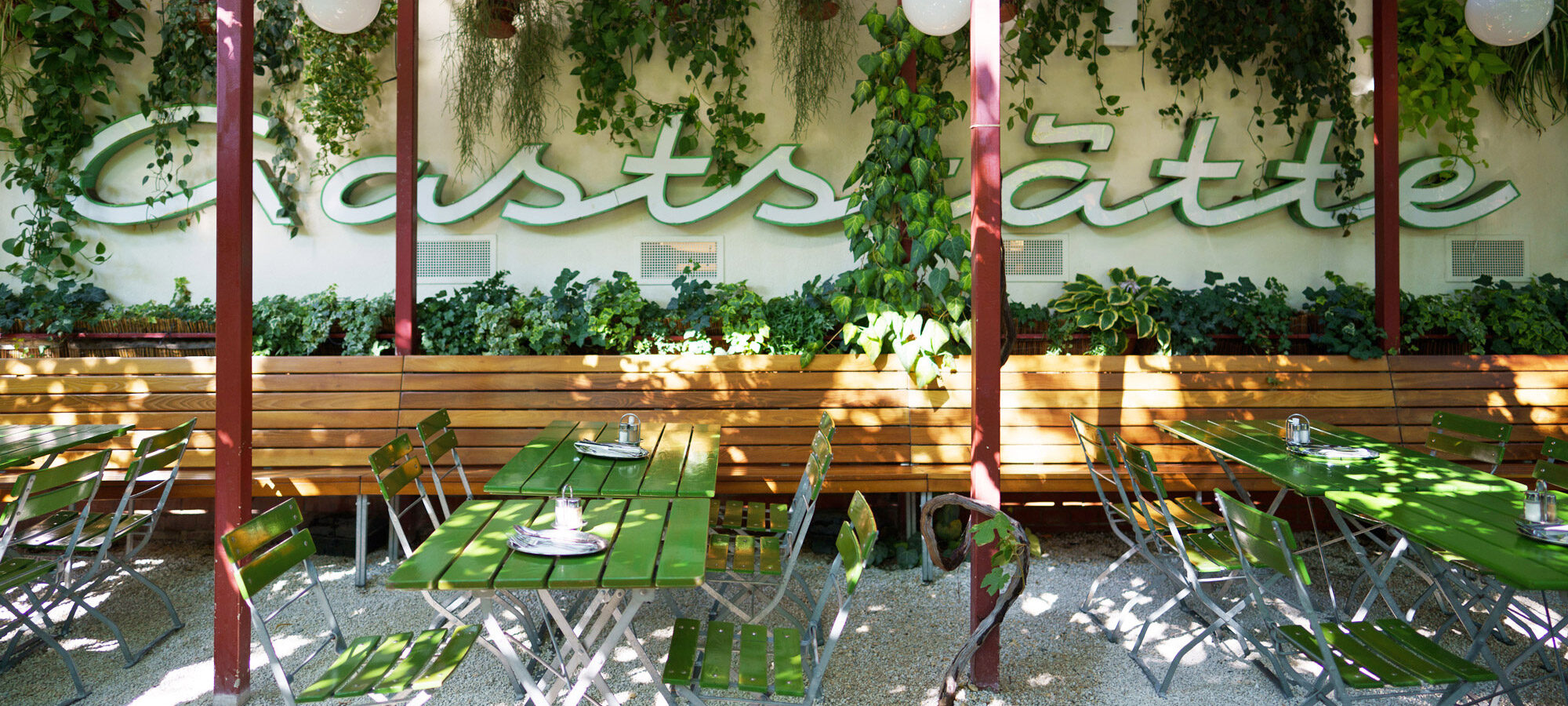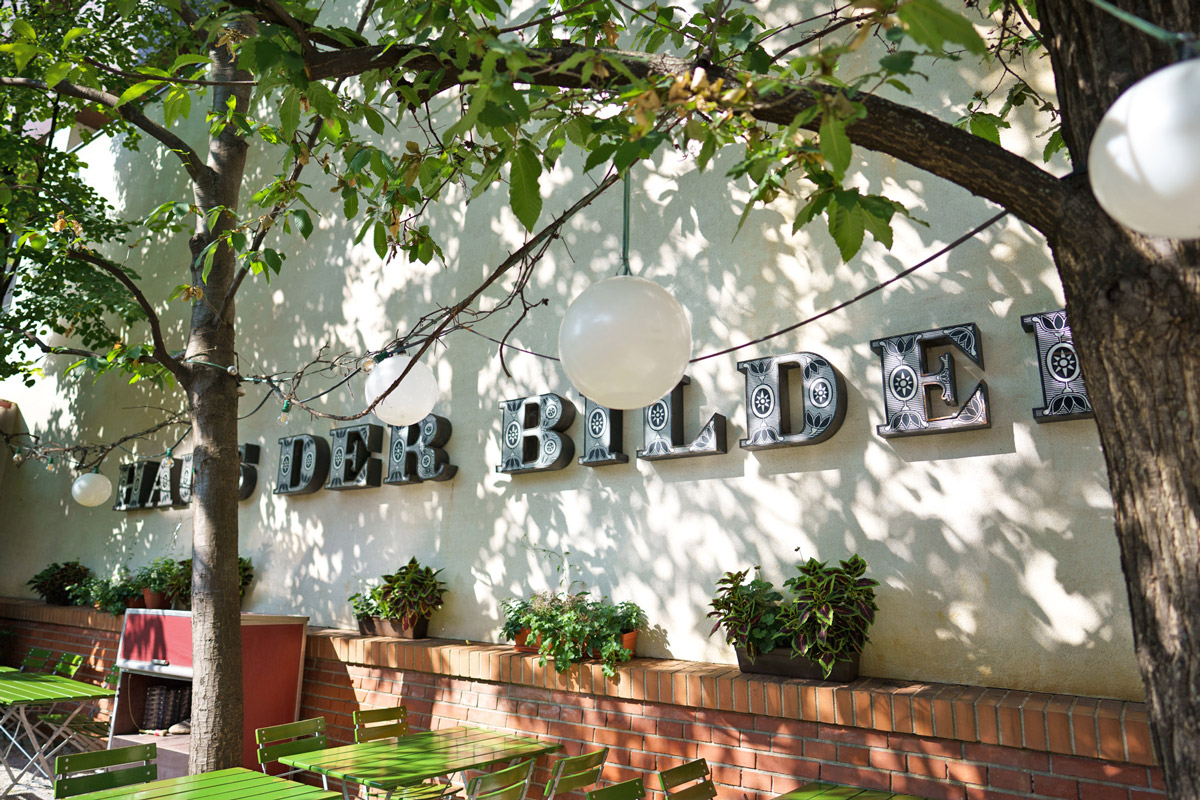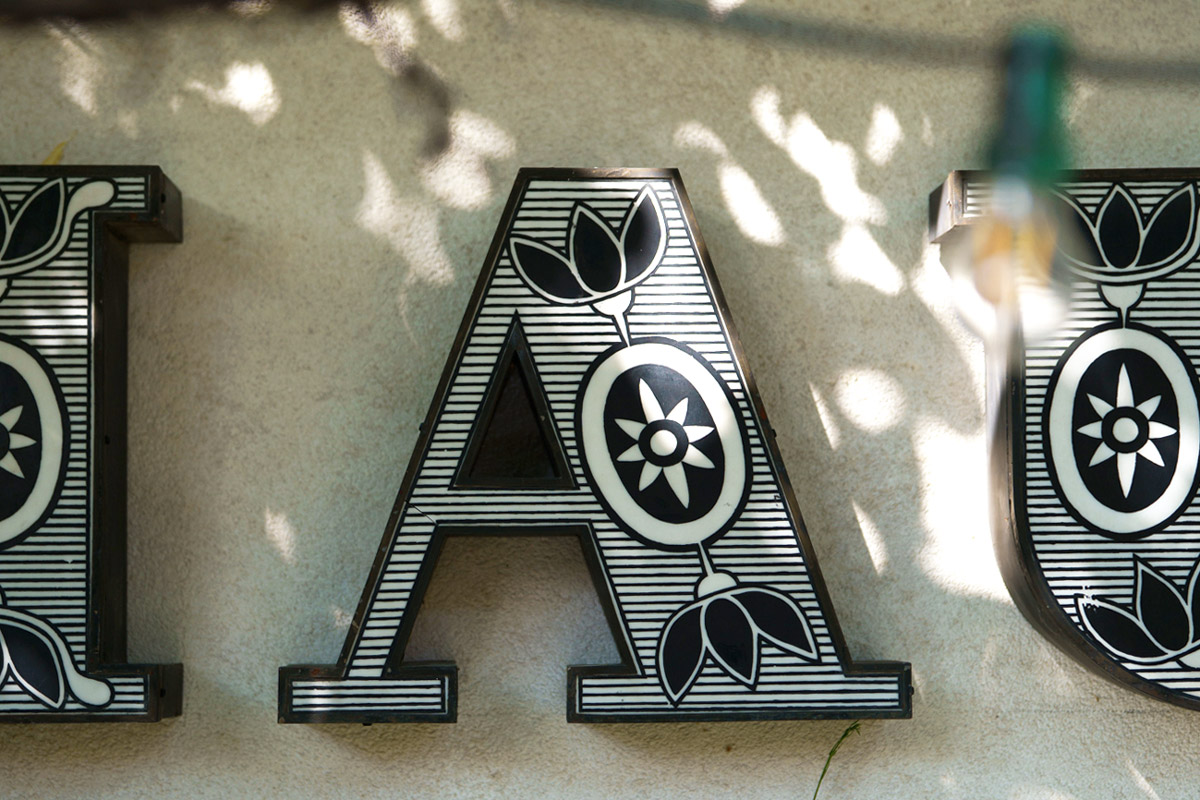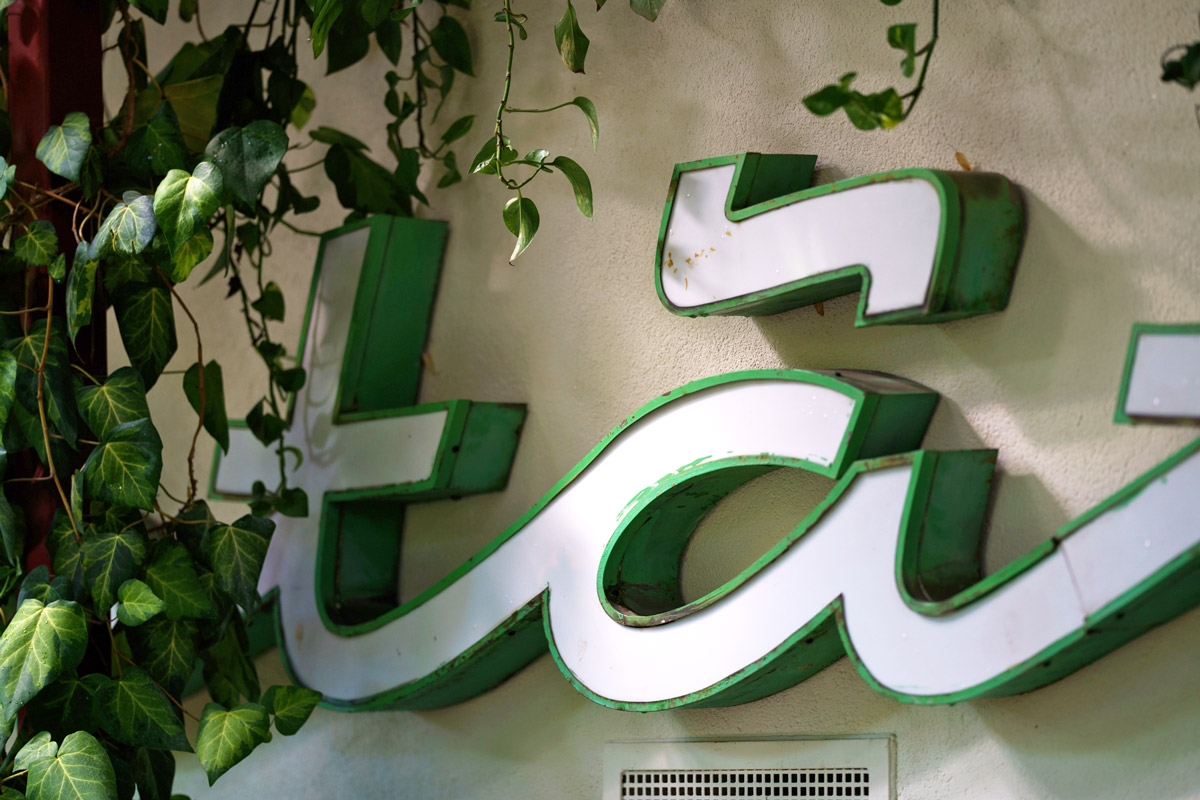
Stadtschrift im Glacis Gastgarten
Seit 2004 wird im Glacis Beisl am Spittelberg die Wiener Wirtshauskultur gepflegt, als Ort des Genusses, des Austauschs und der Beständigkeit inmitten eines sich wandelnden urbanen Raums. Wir wurden 2025 eingeladen, die langen Wände des Gastgartens mitzugestalten. Neben dem aus Hernals stammenden Gaststätte-Schriftzug wurde dafür das HAUS DER BILDER ausgewählt, das ursprünglich seinen Platz in unmittelbarer Nähe, an der Rückseite des Nachbargebäudes in der Breite Gasse hatte.
Gaststätte Schmidt
Schon um 1890 wurde in diesem Haus eine Gastwirtschaft betrieben, das Gasthaus »Zum Ölberg«. Die Hernalser Hoteliersfamilie Jäger führte den Betrieb bis 1954, als Johann Schmidt die Konzession übernahm. 1982 ging die Gaststätte an dessen Sohn über. Vermutlich zu diesem Anlass wurde die „Gaststätte Weinhaus Schmidt“ Beschriftung installiert, in zu dieser Zeit vorherrschender Ausführung mit innenliegenden Leuchtstoffröhren. Mangels Nachfolger kam es 2012 zur Schließung und ein Kindergarten zog in die Räumlichkeiten ein.
Haus der Bilder
Der Kunstsammler Helmut Klewan war als Galerist seit den 1970ern in Wien und München aktiv. Im »Haus der Bilder« zeigte er ab 2004 monatlich neue Ausstellungen mit Werken aus seiner Sammlung. 2012 wechselte das Haus den Besitzer. Eine geplante Renovierung kam nicht zustande, seither ist die Zukunft des Gebäudes ungewiss. Fünf Jahre nach ihrer Demontage kehrten die charakteristischen, ornamental von Hand bemalten Buchstaben wieder in unmittelbare Nähe ihres Ursprungsorts zurück: an die Rückseite des Nachbargebäudes, in den Gastgarten des Glacis Beisl.